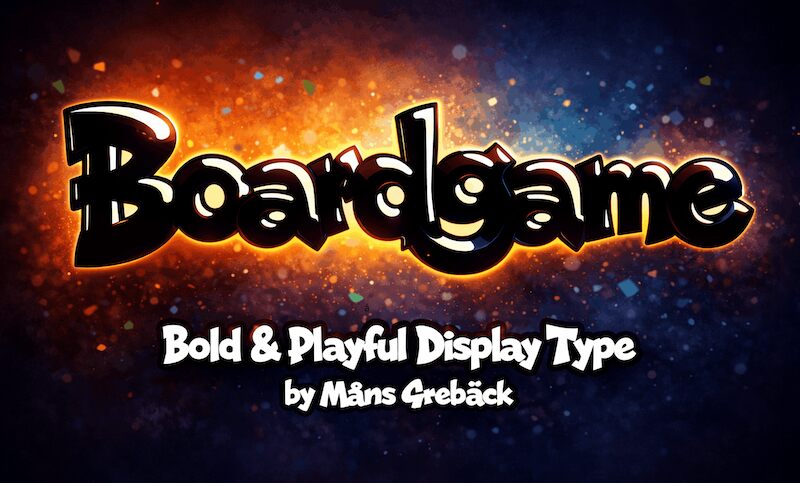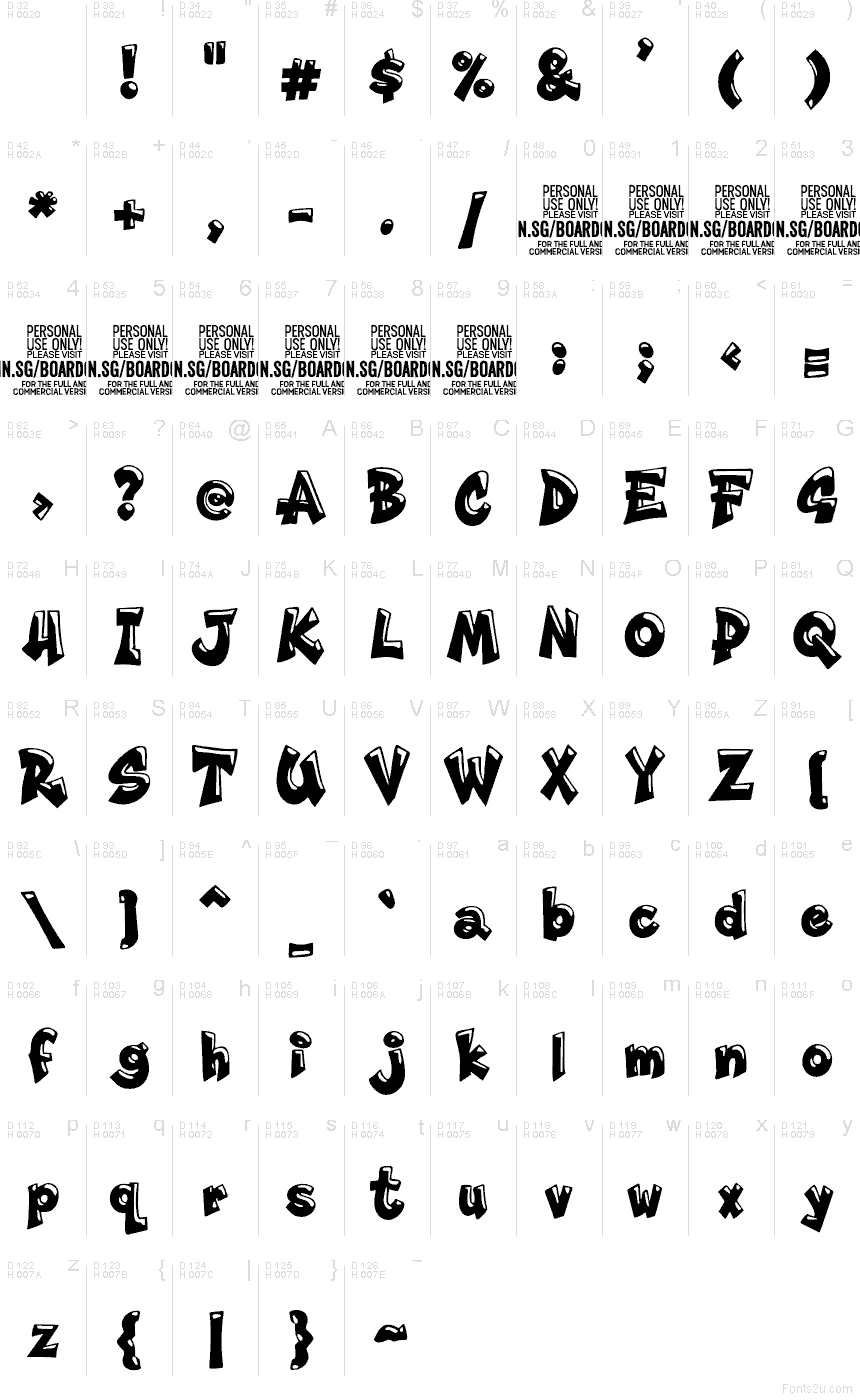
Boardgame PERSONAL USE Regular
Boardgame من Mans Greback AB هو خط عرض مجاني بأسلوب الرسوم المتحركة. شكله المنتفخ المسحوب للداخل يمنح كل حرف مظهراً ممتلئاً ومضغوطاً قليلاً في المنتصف. التفاعل بين المنحنيات الخارجية الدائرية والزوايا الحادة يضفي على الحروف طاقة مرحة، مما يجعلها أنسب لعلامات الألعاب العائلية منها لأسلوب القصص المصورة التقليدي.
يُعد خط Boardgame مثالياً لدعوات الحفلات، وتغليف منتجات الأطفال، وعناوين ألعاب الطاولة، وصور مصغرة على YouTube، والملصقات المدرسية، حيث يمكن لإيقاعه المفعم بالحيوية والضخم أن يبرز العناوين القصيرة. كما تساعد أشكاله المبالغ فيها في إطالة تصاميم الملصقات ولافتات التطبيقات والبضائع الترفيهية دون الحاجة إلى زخارف إضافية لتحديد الطابع العام.